増補新装版 篆書デザイン
グラフィック社は、小田切草雲氏著書による、古代文字を現代に活かす視点を提示した書籍「増補新装版 篆書デザイン」を2024年5月に発売する。
古代書体のひとつ「篆書」をデザインに応用する手引「増補新装版 篆書デザイン」
古代中国から伝わる漢字のスタイルのひとつ、「篆書(てんしょ)」。
今では印章や碑銘など限られた場面でしか用いられない篆書を、店舗や企業のロゴから、SFファンタジー作品のタイトルなど、現代のデザインに応用するための発想について実例を交えて解説。
1972年刊の原著に論考、事例を増補した新装版となる。
「増補新装版 篆書デザイン」イメージ
◆篆書の基本 用筆と運筆
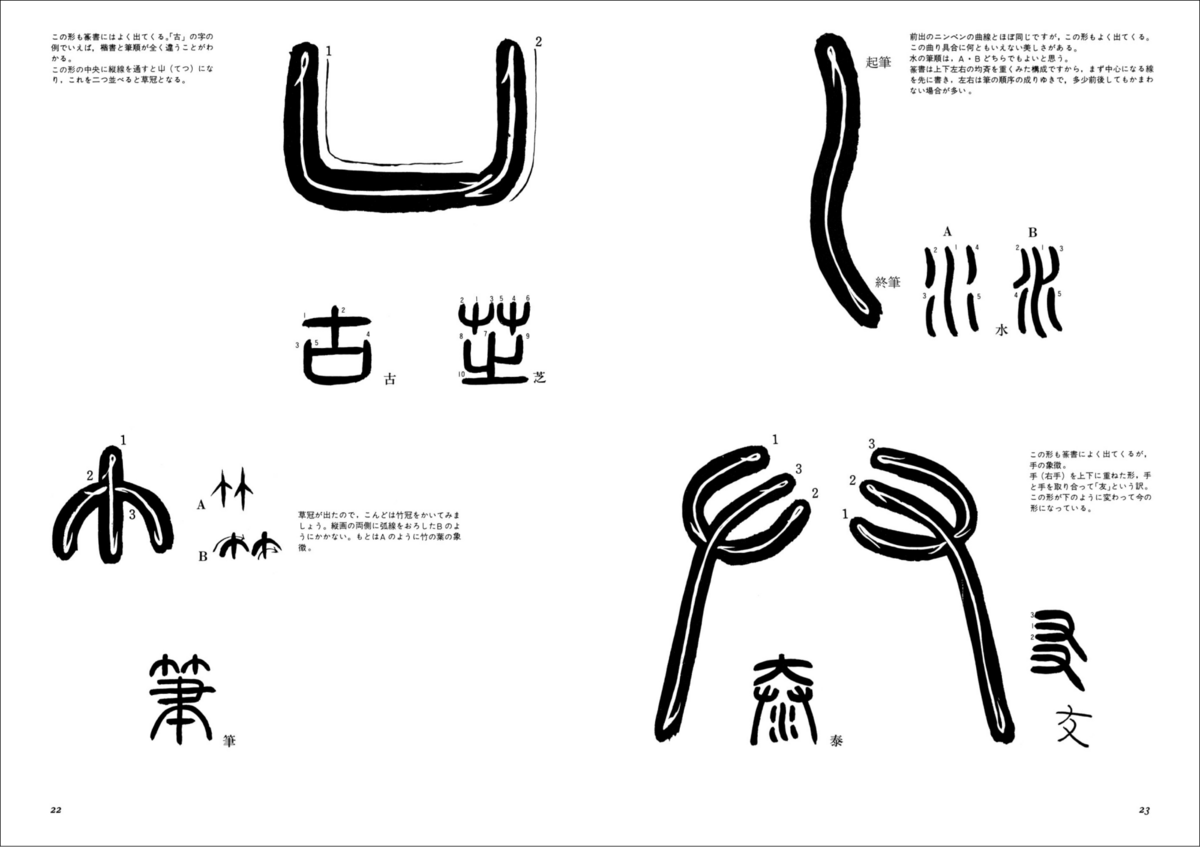
◆篆書の構成 シンメトリー
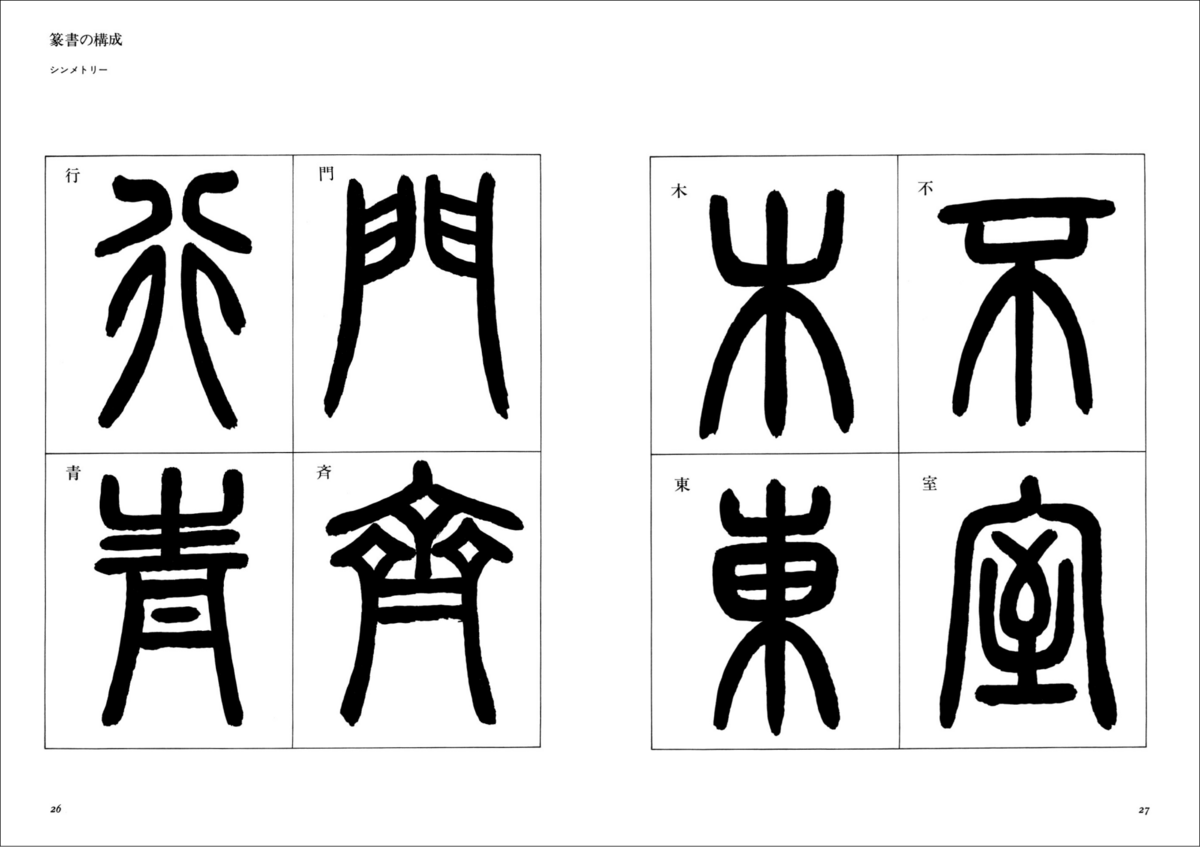
◆街に拾う篆書
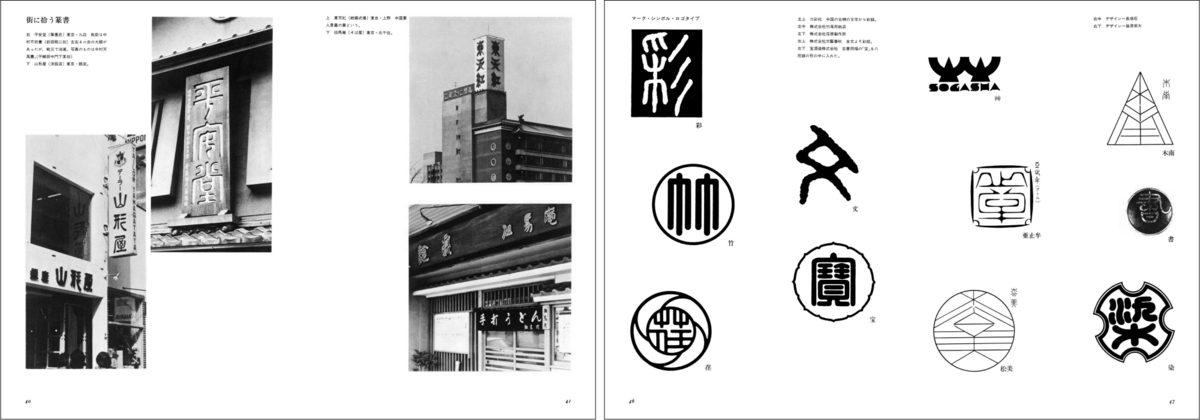
◆漢字のデザイン
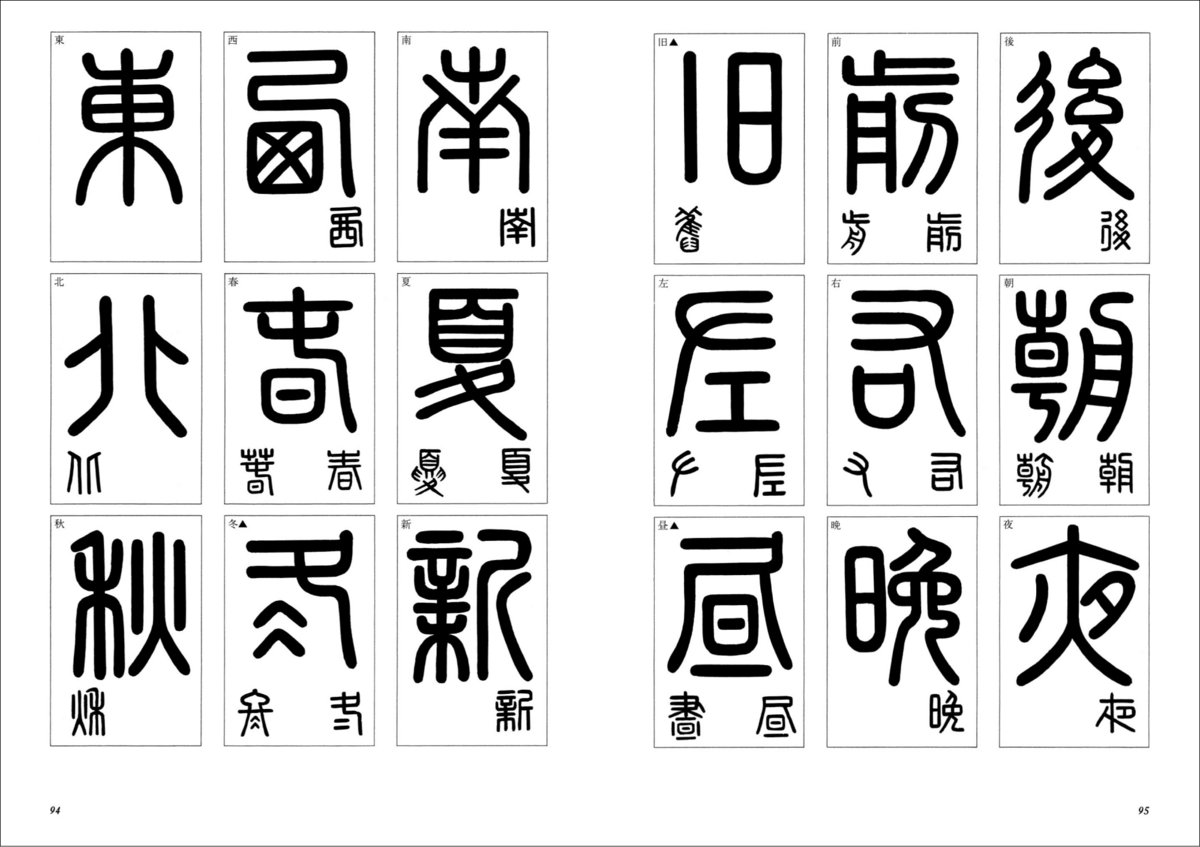
◆篆刻
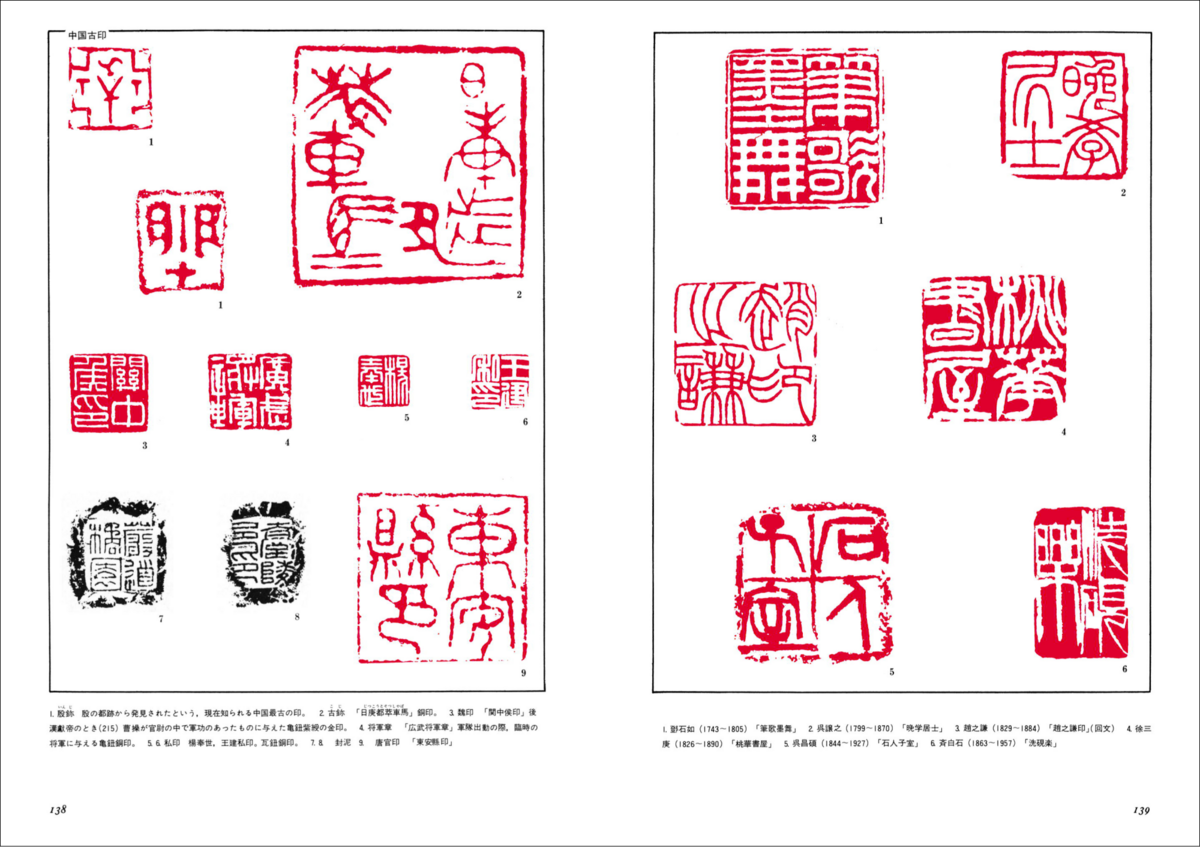
◆現代の篆書系ロゴデザイン
「増補新装版 篆書デザイン」目次
はじめに 歴史と基本:漢字の誕生/篆書と現代/篆書デザインの用具/用筆と運筆/篆書の構成 ●応用と展開/瓦当/江戸の篆書デザイン/街に拾う篆書/グラフィック・エレメントとしての篆書/素材によるバリエーション ●書体デザイン:ひらがなのデザイン/カタカナのデザイン/漢字のデザイン/ ●篆刻への招待:篆刻とは/用具/さあ彫ってみよう ●増補:古賀弘幸「「篆書デザイン」のありか─聖性と装飾」/現代の篆書系ロゴデザイン/篆書系フォントの世界